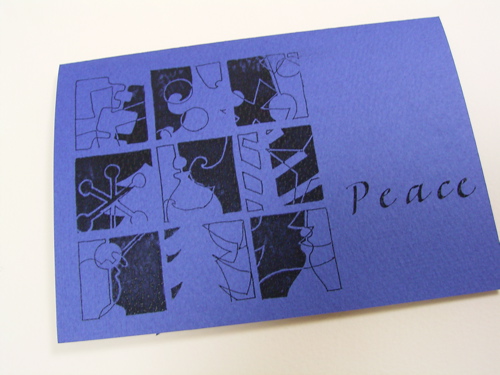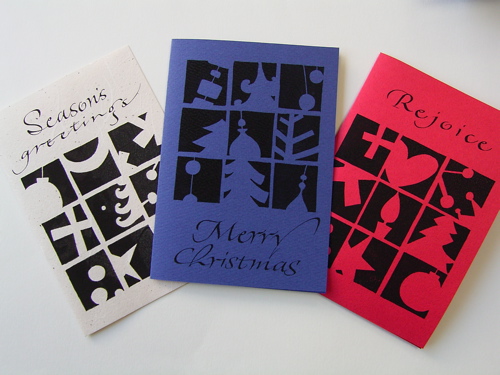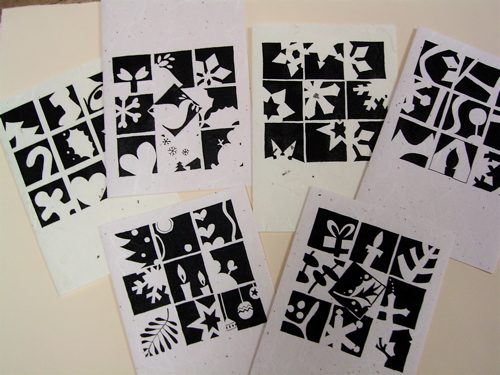
今年のクリスマスカード
今年クラスで作るクリスマスカードは、9個のクリスマスのモチーフを切り絵風にデザイン化したものです。
ちょこっとだけ大人っぽくしたいので、形すべてではなく、その一部分だけを切り取りました。PCを使えばもっと簡単に仕上がるでしょうが、ここはゆっくりと手作業です。漫画家のアシスタントの様に面相筆でべた塗り!はみ出しても修正液があるから、大丈夫。
きちんと時間をかけて原稿を作れば、あとは手差しコピーで大量生産可能
。でも、カリグラファーとしては、やっぱり文字だけは手書きにしたらいいかもしれませんね〜。
クラスの生徒さんの分だけ次々と新しいデザインが生まれてくるので、一枚ずつコピーを取らせてもらっています。すべてお見せ出来ないのが残念です
ちょこっとだけですが、昨日の午前クラスの方の分をご紹介。
クリスマスなのに白黒のモノトーンですが、とても素敵です。所々反転していたり、傾いていたり、文字になっていたり、デザインはいくらでも応用が利きます。
和紙にコピーをすると、あら、和風な感じでピッタリ。
こんな風にデザインを複雑にしていっても楽しいですね。